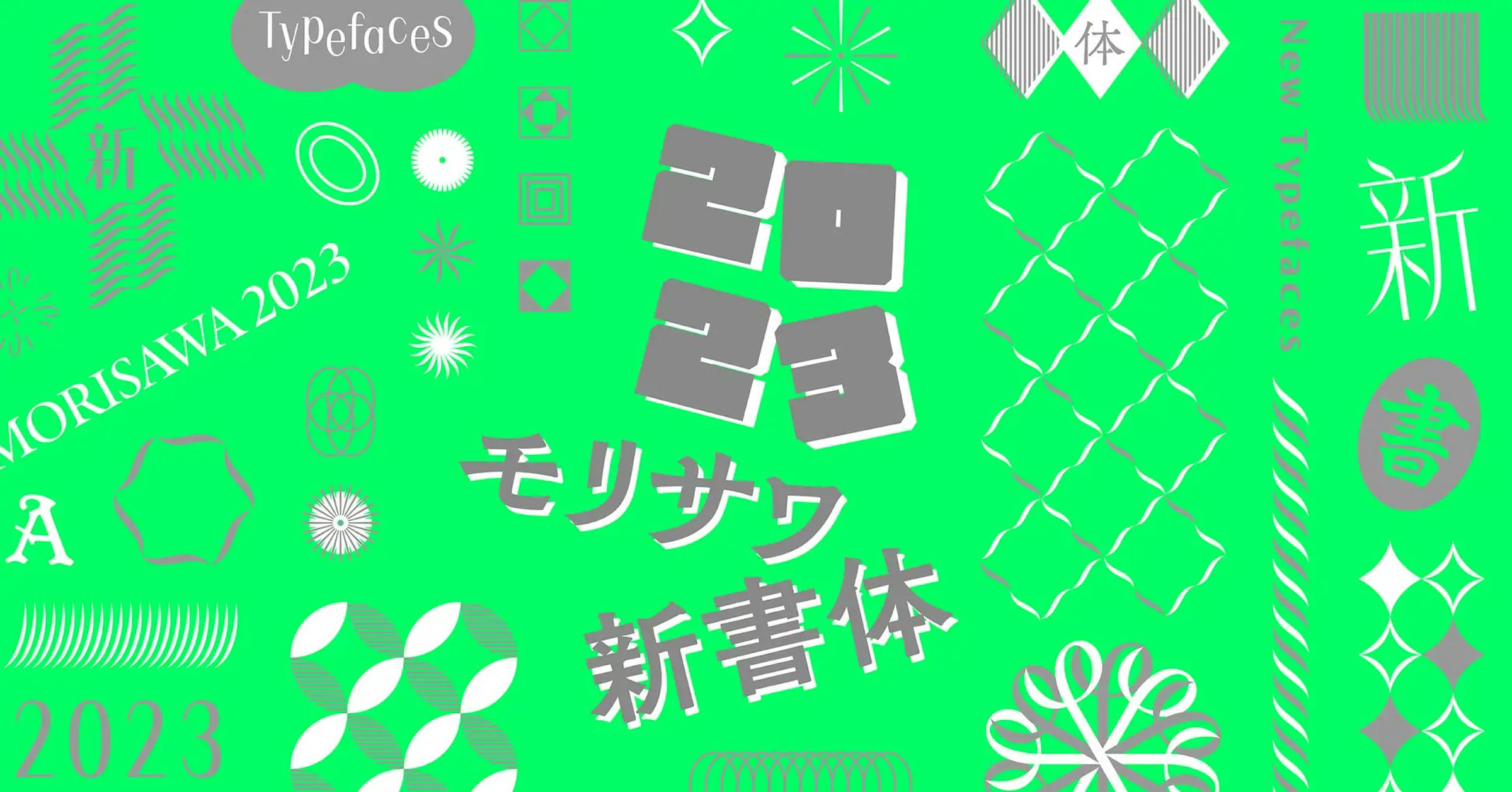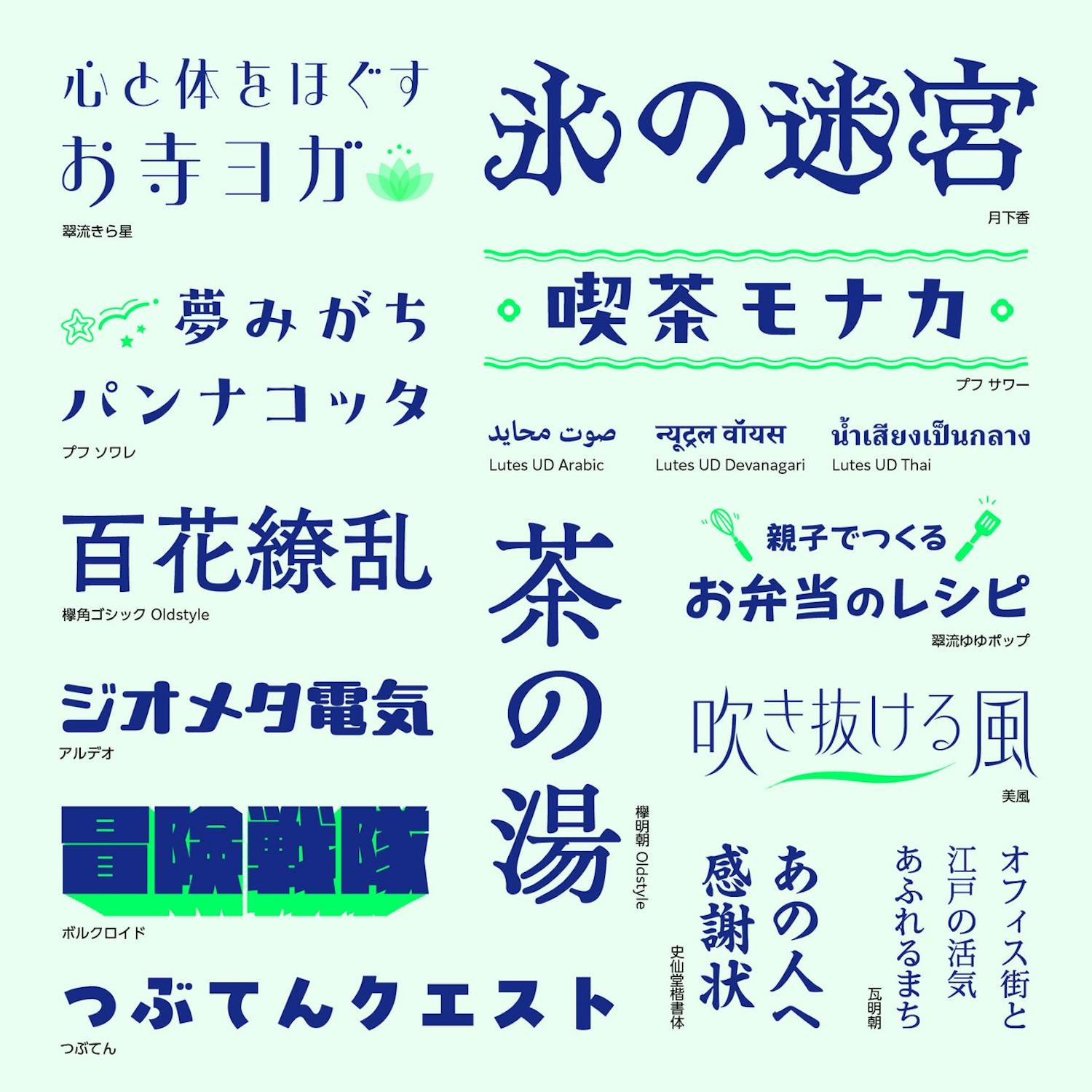
モリサワ、「欅明朝 Oldstyle」など2023年秋にリリースする新書体を一部発表
モリサワは、2023年秋に新書体をリリースする予定だと発表しました。今回発表された新書体は全16ファミリーで、広告や動画のテロップなどに使用することを想定してデザインされたものが多く取り揃えられています。エッジの効いたデザインの「ボルクロイド」、幾何学的で丸みのあるデザインの「アルデオ」、可愛らしいデザインの「つぶてん」、ミステリアスなデザインの「月下香(げっかこう)」など個性的な書体が揃っています。
この中でも特に注目なのが、金属活字からインスピレーションを受けた「欅明朝 Oldstyle」。「欅角ゴシック Oldstyle」も合わせてリリースされ、上品でやわらかい印象を与えてくれます。さらに、小さく自由な字形で好評だった「プフ」シリーズからは「プフサワー」と「プフソワレ」が登場。レトロな雰囲気とキャッチーな明るさが特長です。
モリサワはこれまで台湾の繁体字のフォントをベースにデザインにも取り組んできており、「美風」はその一例で、台湾の玉川設計所が手掛ける繁体字を基に作られました。また台湾の子会社Arphic Typesの書体の漢字を用いた「翠流きら星」、「翠流ゆゆポップ」もリリース予定です。